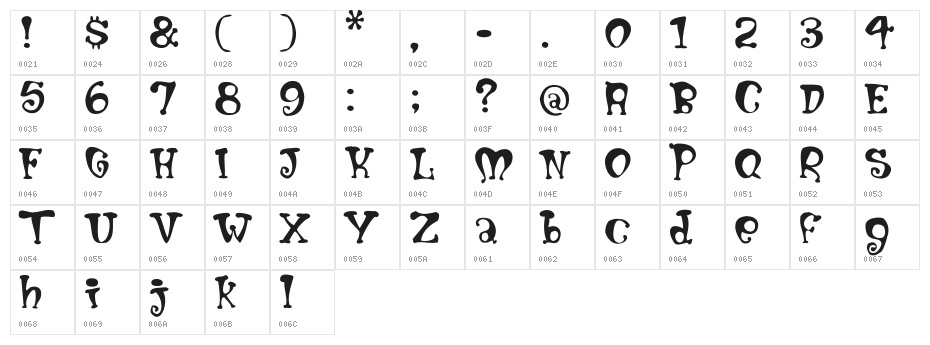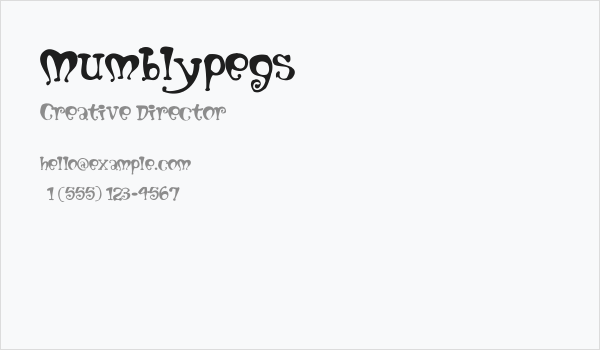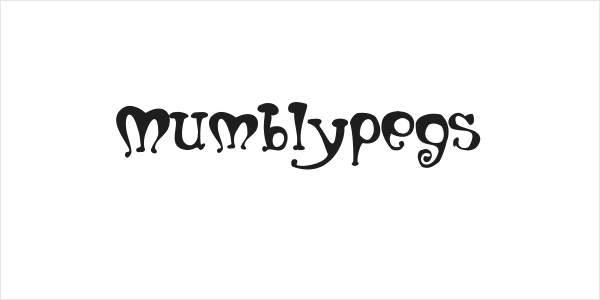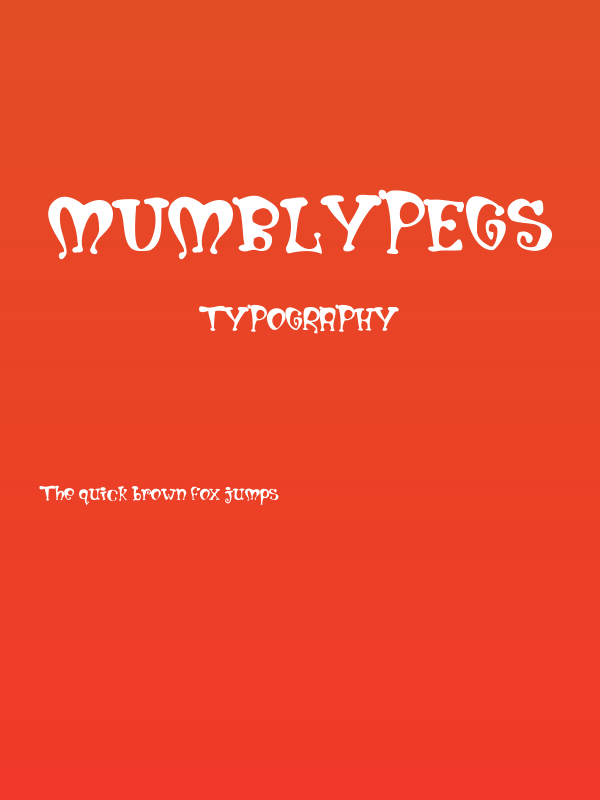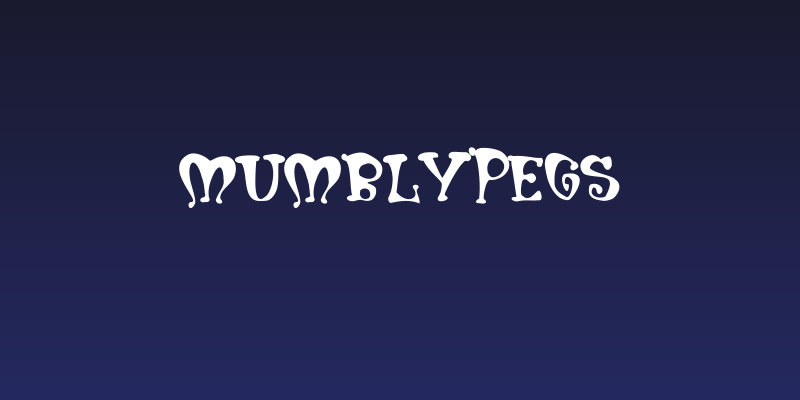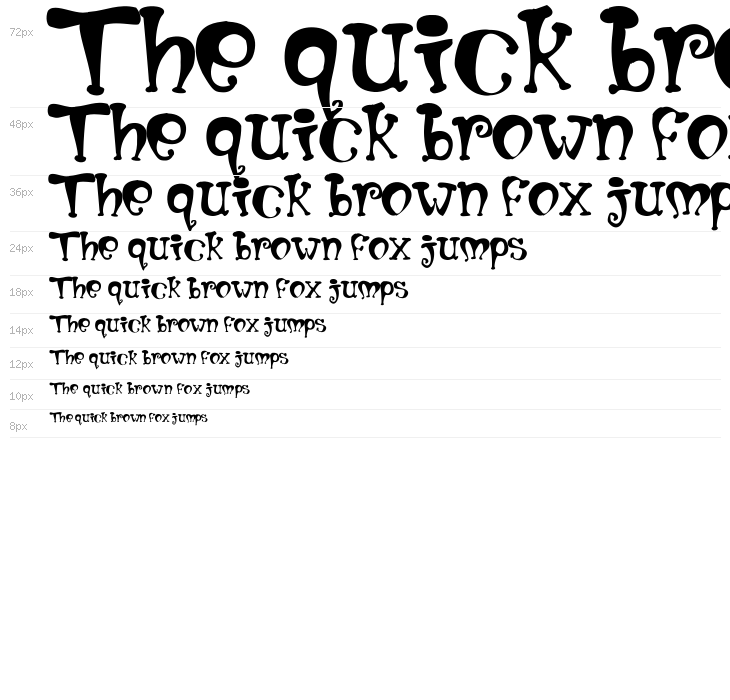
Mumblypegs Font
| 整体风格 | Playful, Whimsical, Creative |
| 推荐项目 | Ideal for children's books, playful branding, party invitations, and creative posters. |